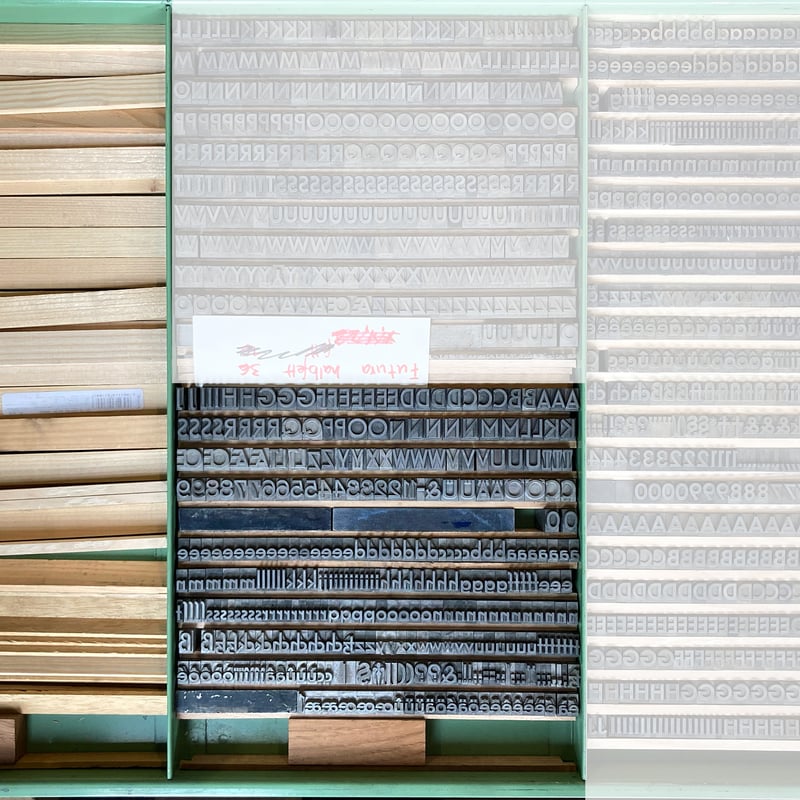
Rhythmus Halbfett
Druckmuster mit Text «Rhythmus Halbfett, 36pt»
Klassifizierung
Sans Serif
Schriftschnitt
Halbfett
Grösse
36 pt / 3 c
Design
Hans Möhring
Jahr
1931
Schriftgiesserei
Schelter & Giesecke
Rhythmus war die Antwort der Schriftgiesserei Schelter & Giesecke auf den Erfolg der Futura. Sie weist einige Ähnlichkeiten zu Kabel (abgewinkelte Abschlüsse), Erbar-Grotesk und Nobel auf und wurde in den drei Schriftschnitten Leicht, Halbfett und Fett angeboten.